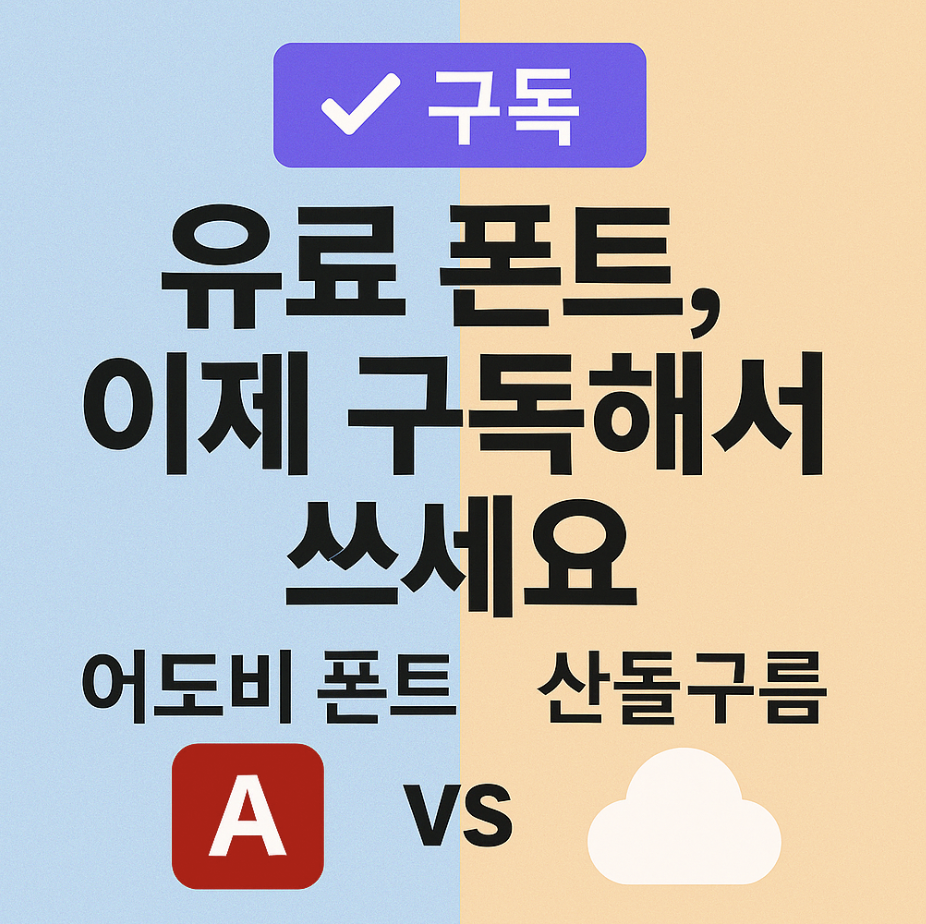
"이 폰트, 상업적으로 이용 가능한가요?" 디자인 작업이나 유튜브 자막을 만들 때마다, 마음속에서 수없이 되뇌는 질문일 겁니다. 저작권 경고장에 대한 막연한 두려움 때문에, 결국 매번 똑같은 무료 폰트만 돌려쓰고 있지는 않으신가요? 개성 있는 결과물을 만들고 싶지만, 수십만 원에 달하는 폰트 하나를 덜컥 구매하기엔 부담스러운 현실.
하지만 이제 그 지긋지긋한 고민을 끝낼 때가 왔습니다. 마치 넷플릭스로 영화를 보듯, 월정액을 내고 수만 가지의 유료 폰트를 마음껏 사용하는 '폰트 구독'의 시대가 열렸기 때문입니다. 오늘은 그 대표적인 두 거인, '어도비 폰트'와 '산돌구름'을 낱낱이 비교하여, 당신의 작업 환경에 딱 맞는 최고의 파트너를 찾아드리겠습니다.
소유의 시대에서 경험의 시대로
과거에 우리가 폰트를 사용하는 방식은 '소유'의 개념이었습니다. 마음에 드는 서체 하나를 발견하면, 큰돈을 주고 라이선스를 구매하여 내 컴퓨터에 영구적으로 설치했죠. 하지만 이 방식은 비용 부담이 크고, 한 번 사면 다른 새로운 글꼴을 사용하기 어렵다는 단점이 있었습니다.
폰트 구독 서비스는 이 모든 패러다임을 바꿨습니다. 매달 커피 몇 잔 값으로, 수천, 수만 종의 고품질 유료 서체를 저작권 걱정 없이 자유롭게 '경험'할 수 있게 된 것입니다. 이는 비용 절감은 물론, 다양한 시도를 통해 내 작업의 수준을 한 단계 끌어올릴 수 있는 가장 현명한 해결책입니다.
글로벌 크리에이터를 위한 선택, 어도비 폰트
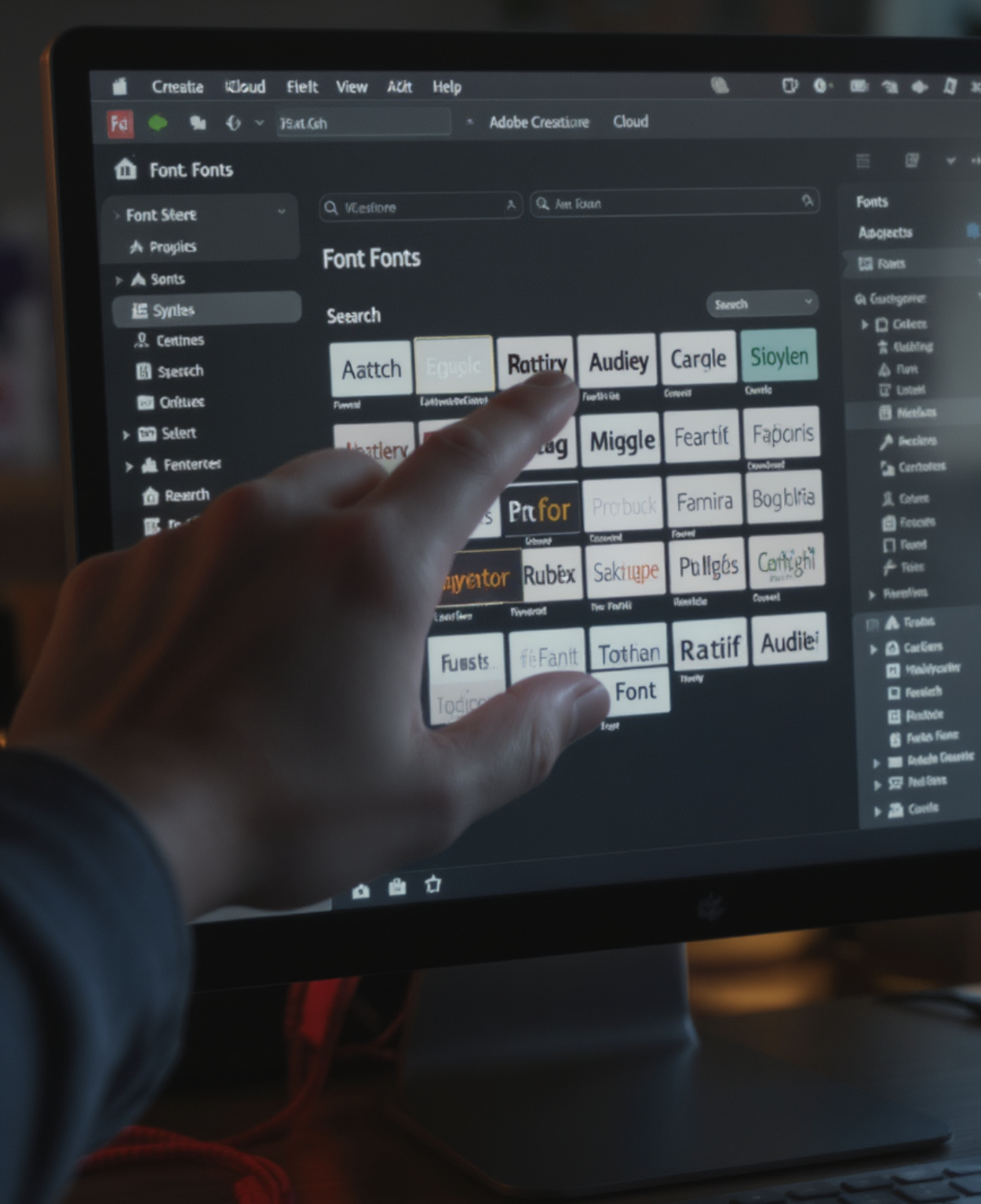
포토샵, 일러스트레이터, 프리미어 프로 등 어도비의 크리에이티브 클라우드(Creative Cloud)를 이미 사용하고 있다면, 당신은 자신도 모르는 사이에 엄청난 보물창고를 가지고 있는 셈입니다. '어도비 폰트(Adobe Fonts)'는 어도비 정품 구독자에게 '무료'로 제공되는 거대한 폰트 라이브러리입니다.
어도비 폰트의 가장 큰 강점은 방대한 '영문 서체'와 어도비 프로그램과의 '완벽한 연동성'에 있습니다. 웹사이트에서 마음에 드는 폰트를 클릭하여 활성화하기만 하면, 별도의 설치 과정 없이 포토샵이나 일러스트에서 즉시 사용할 수 있는 마법 같은 편리함을 자랑합니다. 글로벌 시장을 타겟으로 하거나, 영문 타이포그래피 작업이 많은 디자이너에게는 이보다 더 좋은 선택은 없습니다.
한글 타이포그래피의 명가, 산돌구름
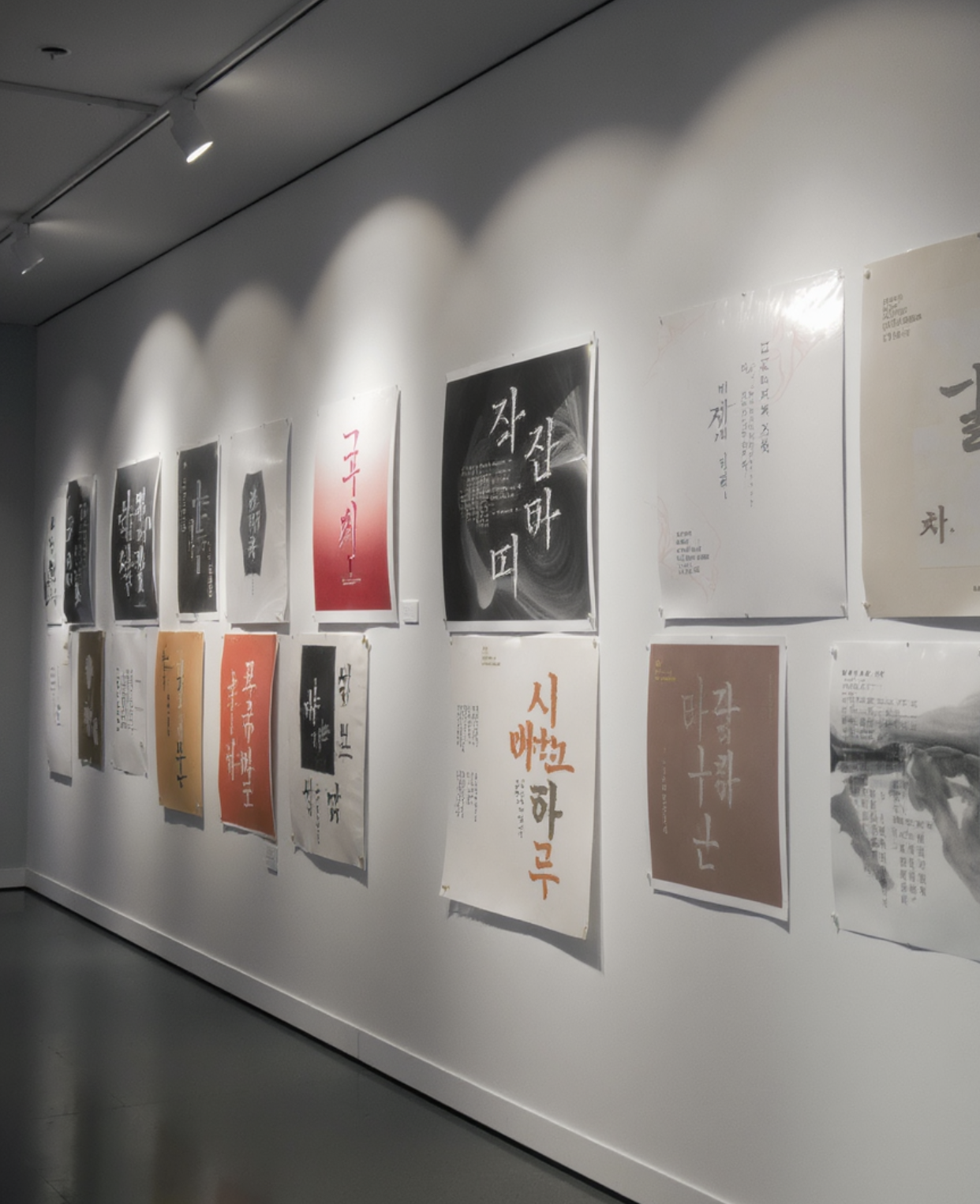
"그럼 한글 폰트는 어디가 최고인가요?" 라는 질문이 나온다면, 대답은 단연 '산돌구름'입니다. 산돌은 대한민국을 대표하는 폰트 디자인 기업으로, 우리가 일상에서 마주하는 수많은 기업 로고와 광고 속의 아름다운 한글 서체를 만들어 온 명가입니다.
산돌구름은 그야말로 '한글 폰트의 정수'를 모아놓은 곳입니다. 감성적인 손글씨체부터, 신뢰감을 주는 본문용 명조체까지, 타의 추종을 불허하는 깊이와 다양성을 자랑합니다. 한글이 중심이 되는 출판, 브랜딩, 영상 콘텐츠 제작자라면, 산돌구름이 제공하는 섬세하고 아름다운 한글 서체들은 당신의 작업에 '영혼'을 불어넣어 줄 것입니다.
편리함의 대결, 자동 활성화 vs 클라우드 다리
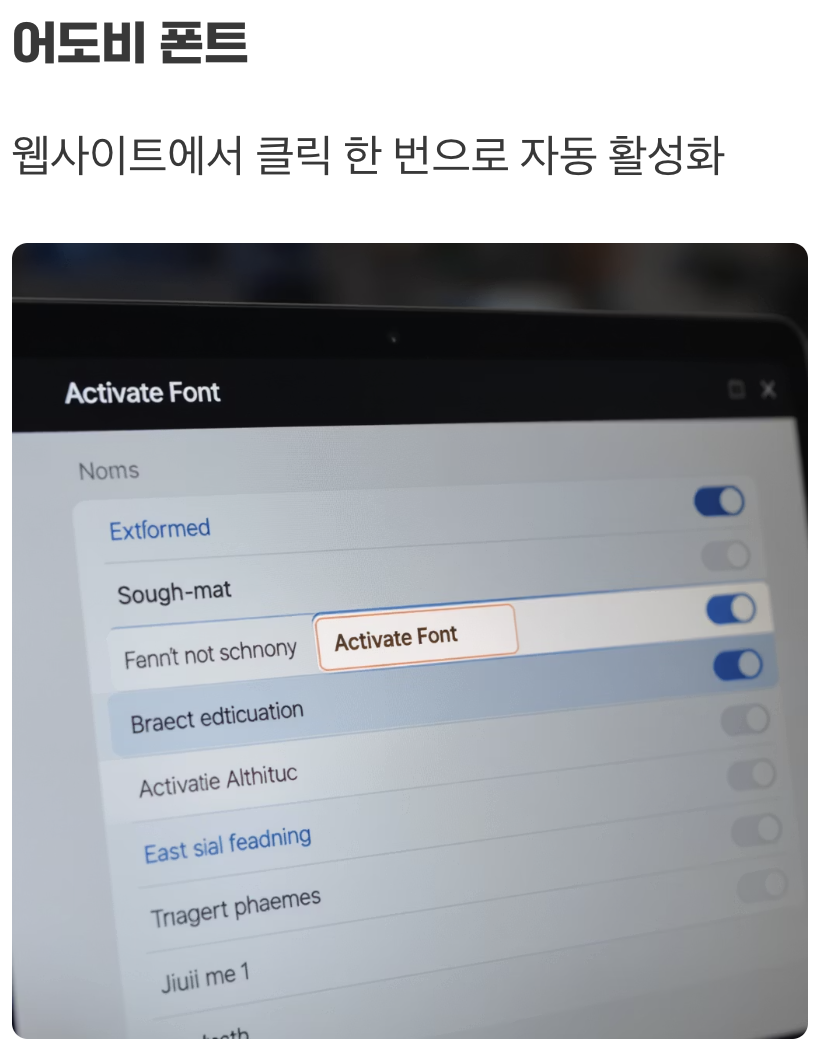
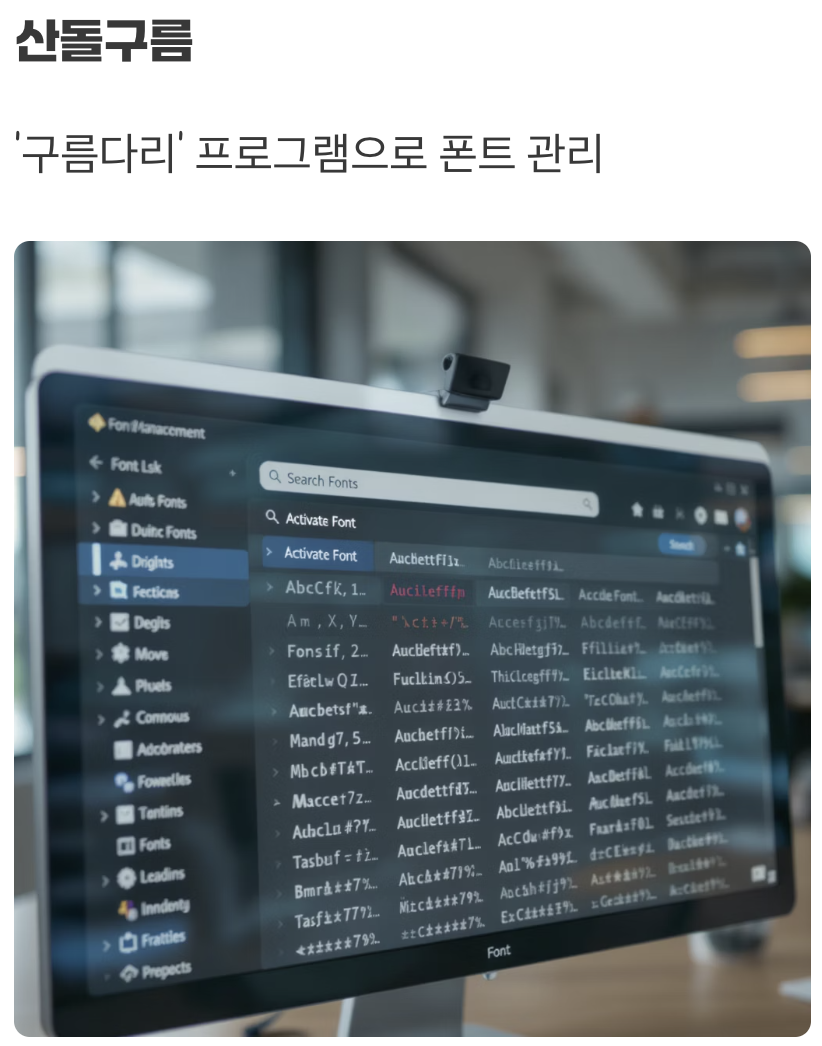
두 서비스의 사용 편의성에는 약간의 차이가 있습니다. 어도비 폰트는 앞서 말했듯, 웹사이트에서 클릭 한 번이면 프로그램에 자동 적용되는 '자동 활성화' 방식이라 매우 직관적입니다. 작업 중 필요한 폰트를 즉시 찾아 바로 적용할 수 있죠.
산돌구름은 '구름다리'라는 전용 프로그램을 컴퓨터에 설치하여 폰트를 관리하는 방식입니다. 이 프로그램을 통해 원하는 폰트를 켜고 끄며 사용하는데, 이 역시 매우 편리하고 안정적입니다. 다만, 별도의 프로그램을 항상 실행해야 한다는 작은 차이가 있습니다.
그래서 진짜 승자는 누구일까?
결론적으로, 두 서비스의 승자는 '누가, 어떤 작업을 하느냐'에 따라 명확하게 갈립니다. 이 질문에 답하는 것이 당신에게 맞는 구독 서비스를 찾는 가장 빠른 길입니다.
만약 당신이 어도비 크리에이티브 클라우드를 구독 중이고, 영문 중심의 디자인이나 글로벌 콘텐츠를 주로 제작한다면, 추가 비용 없이 제공되는 '어도비 폰트'가 압도적으로 유리합니다. 하지만 당신의 작업 무대가 한국이고, 섬세하고 완성도 높은 '한글' 타이포그래피가 무엇보다 중요하다면, '산돌구름'은 대체 불가능한 최고의 선택입니다.